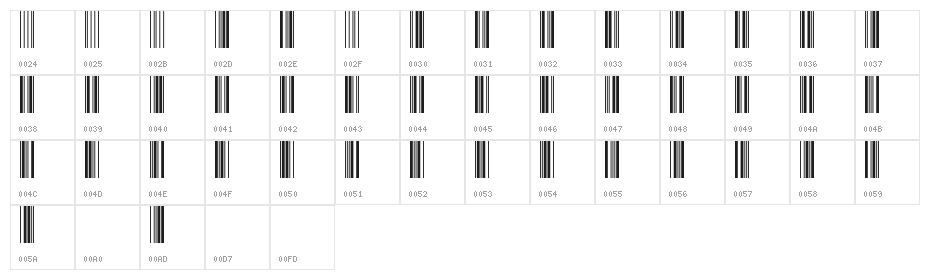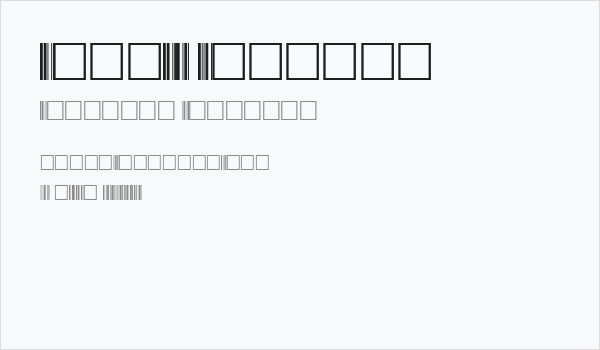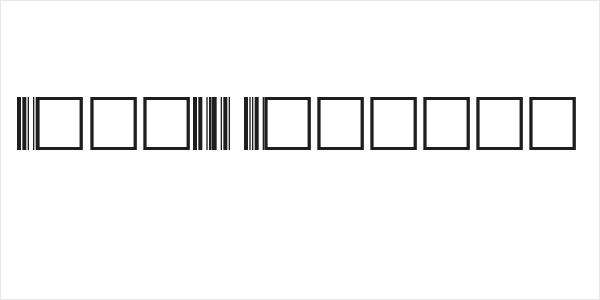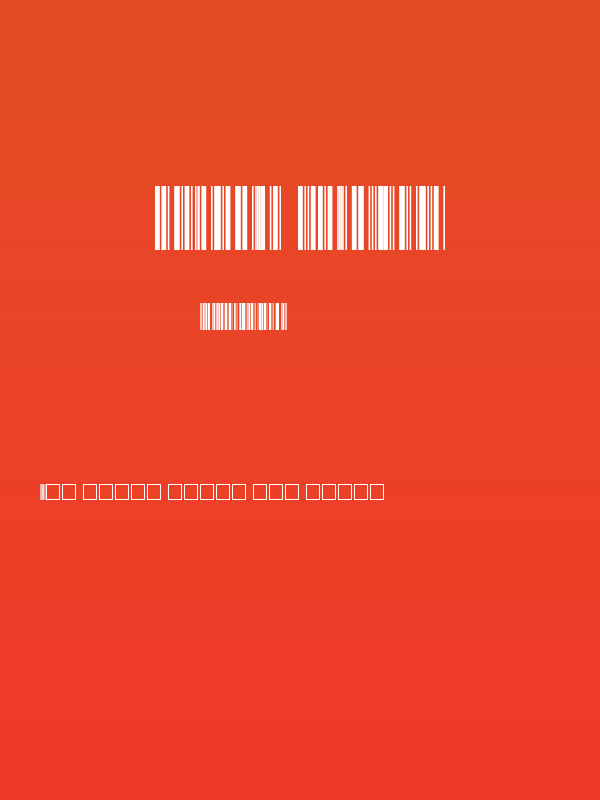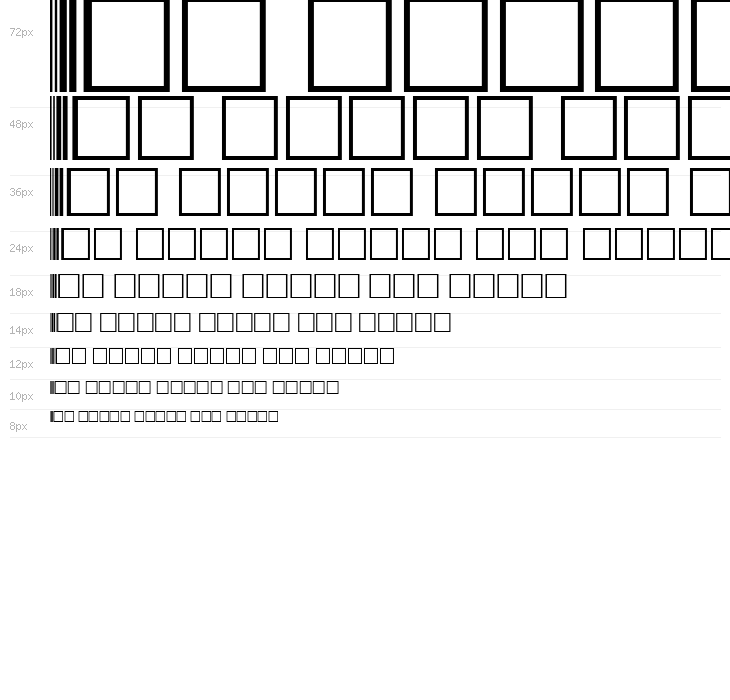
Code39 Regular Font
| الاسم | Code39 Regular |
| عدد المحارف: | 48 |
| الفئات | Dingbats |
| النمط العام | Utilitarian |
| حالة الاستخدام | Barcodes, Inventory labels, Shipping labels |
| مشاريع مقترحة | Ideal for product labeling, inventory management, and shipping logistics where barcode scanning is required. |